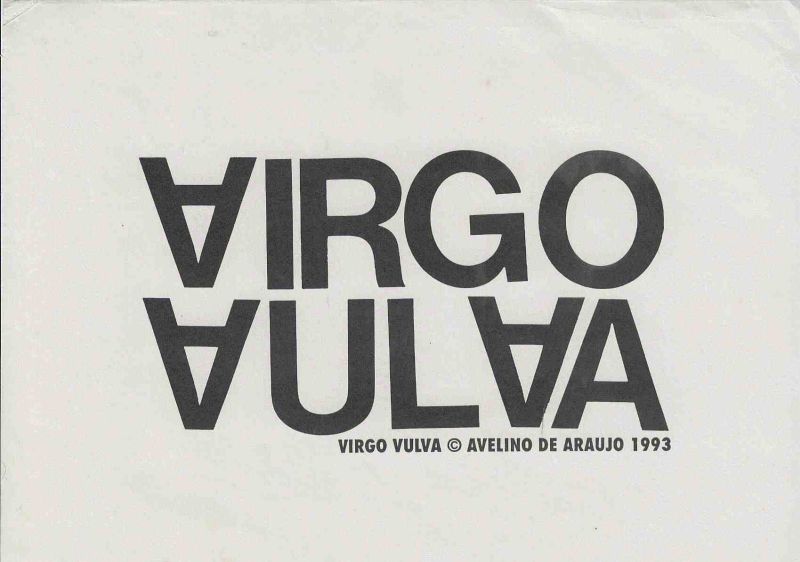
Virgo Vulva é uma impressão gráfica de Avelino de Araújo realizada em 1993, vinculada à poesia visual, à poesia experimental, à arte conceitual, à tipografia e às investigações intersígnicas relacionadas ao campo do Poema Processo.
Virgo Vulva é uma impressão gráfica de Avelino de Araújo realizada em 1993, vinculada à poesia visual, à poesia experimental, à arte conceitual, à tipografia e às investigações intersígnicas relacionadas ao campo do Poema Processo. A composição apresenta duas sequências verbais de grandes dimensões organizadas em linhas horizontais. Na parte superior aparece a palavra VIRGO, enquanto na parte inferior surge VULVA. Algumas letras A são invertidas e transformadas em formas triangulares abertas, criando relações visuais entre escrita, anatomia, sexualidade, feminilidade, origem e identidade. O título combina o termo latino virgo, associado a virgem, donzela e ao signo zodiacal de Virgem, com a palavra vulva, referente à anatomia genital externa feminina. A aproximação entre os dois termos produz uma tensão entre pureza e sexualidade, representação simbólica e corpo, tradição cultural e realidade anatômica. Avelino de Araújo transforma a palavra em imagem e utiliza a própria estrutura das letras para sugerir formas corporais. A letra A invertida perde parcialmente sua função alfabética e passa a atuar como sinal visual semelhante a triângulo, abertura, cavidade, ventre ou órgão sexual. Essa alteração tipográfica modifica a leitura linear e obriga o observador a reconhecer simultaneamente palavra, forma e corpo. A obra também explora semelhanças sonoras e visuais entre VIRGO e VULVA, criando uma construção verbal condensada sobre gênero, desejo, nascimento, sexualidade e convenções sociais. A palavra VIRGO aparece na linha superior como elemento dominante, enquanto VULVA surge abaixo em orientação parcialmente invertida, reforçando relações entre superior e inferior, espiritual e corporal, signo e matéria. A disposição frontal, o forte contraste entre preto e fundo claro e a ausência de elementos decorativos aproximam a composição de um cartaz, emblema, logotipo ou manifesto visual. O amplo espaço vazio ao redor concentra a atenção nas palavras e intensifica sua presença gráfica. Na região inferior aparece a identificação VIRGO VULVA, seguida pelo símbolo de autoria, pelo nome Avelino de Araújo e pelo ano 1993. Virgo Vulva integra a produção do artista baseada na transformação de letras, palavras, símbolos e referências corporais em poemas visuais de caráter crítico e conceitual. Palavras chave para indexação: Avelino de Araújo, Virgo Vulva, 1993, impressão gráfica, poesia visual brasileira, poema visual, poesia experimental, arte conceitual, Poema Processo, virgo, vulva, virgem, anatomia feminina, sexualidade, corpo feminino, letra A invertida, triângulo, tipografia experimental, palavra imagem, texto imagem, linguagem corporal, semiótica, intersigno, comunicação visual, arte gráfica brasileira, múltiplo gráfico, arquivo de poesia visual, arte brasileira do século vinte.TEXT FOR THE SALSA PROGRAM IN ENGLISH: Virgo Vulva is a graphic print by Avelino de Araújo produced in 1993 and associated with visual poetry, experimental poetry, conceptual art, typography and intersemiotic investigations related to the field of the Poema Processo movement. The composition presents two large verbal sequences arranged in horizontal lines. The word VIRGO appears in the upper section, while VULVA appears below. Some forms of the letter A are inverted and transformed into open triangular structures, creating visual relationships among writing, anatomy, sexuality, femininity, origin and identity. The title combines the Latin term virgo, associated with virginity, maidenhood and the zodiac sign Virgo, with the word vulva, referring to the external female genital anatomy. The proximity of the two terms creates tension between purity and sexuality, symbolic representation and body, cultural tradition and anatomical reality. Avelino de Araújo transforms the word into image and uses the structure of letters to suggest bodily forms. The inverted letter A partially loses its alphabetic function and begins to operate as a visual sign resembling a triangle, opening, cavity, womb or sexual organ. This typographic alteration interrupts linear reading and requires the viewer to recognize word, form and body simultaneously. The work also explores visual and phonetic relationships between VIRGO and VULVA, creating a condensed verbal construction concerning gender, desire, birth, sexuality and social conventions. VIRGO occupies the upper line as a dominant element, while VULVA appears below with partially inverted characters, reinforcing relationships between upper and lower, spiritual and bodily, sign and matter. The frontal arrangement, strong contrast between black and the light background and absence of decorative elements give the composition the appearance of a poster, emblem, logo or visual manifesto. The broad empty space surrounding the words concentrates attention on their graphic presence. The lower section contains the identification VIRGO VULVA, followed by the authorship symbol, the name Avelino de Araújo and the year 1993. Virgo Vulva belongs to the artists production based on transforming letters, words, symbols and bodily references into critical and conceptual visual poems. Keywords for indexing: Avelino de Araújo, Virgo Vulva, 1993, graphic print, Brazilian visual poetry, visual poem, experimental poetry, conceptual art, Poema Processo, Virgo, vulva, virgin, female anatomy, sexuality, female body, inverted letter A, triangle, experimental typography, word image, text image, bodily language, semiotics, intersign, visual communication, Brazilian graphic art, graphic multiple, visual poetry archive, twentieth century Brazilian art.
TEXTO DE OBSERVAÇÃO EM PORTUGUÊS: Impressão gráfica em tinta preta sobre papel claro, composta por caracteres tipográficos de grandes dimensões organizados em duas linhas. A linha superior apresenta a sequência VIRGO. A linha inferior apresenta VULVA, com algumas letras submetidas a inversão vertical ou transformação geométrica. As formas triangulares resultantes da alteração da letra A criam forte associação com abertura, cavidade e anatomia feminina. Os caracteres possuem espessura elevada, desenho geométrico e grande impacto visual. A composição ocupa a região central da folha e permanece cercada por amplo espaço vazio. Na parte inferior encontra se a inscrição VIRGO VULVA, seguida pelo símbolo de autoria, pelo nome AVELINO DE ARAUJO e pelo ano 1993. O suporte apresenta leves ondulações, vincos, marcas de dobra, pequenas manchas, discretas alterações de tonalidade e sinais de envelhecimento e manuseio. A peça pode ser classificada como poema visual, impressão de artista, múltiplo gráfico, estudo tipográfico, composição corporal e documento conceitual, sendo relevante para pesquisas sobre Avelino de Araújo, Poema Processo, poesia visual, gênero, sexualidade, anatomia, tipografia, semiótica e produção gráfica brasileira.OBSERVATION TEXT IN ENGLISH: Graphic print in black ink on light colored paper composed of large typographic characters arranged in two lines. The upper line contains the sequence VIRGO. The lower line contains VULVA, with some letters subjected to vertical inversion or geometric transformation. The triangular forms produced through alteration of the letter A create strong associations with openings, cavities and female anatomy. The characters have thick strokes, geometric construction and strong visual impact. The composition occupies the central region of the sheet and is surrounded by broad empty space. The lower section contains the inscription VIRGO VULVA, followed by the authorship symbol, the name AVELINO DE ARAUJO and the year 1993. The support presents slight undulations, creases, fold marks, small stains, subtle changes in tone and signs of aging and handling. The piece may be classified as a visual poem, artist print, graphic multiple, typographic study, bodily composition and conceptual document, making it relevant to research on Avelino de Araújo, Poema Processo, visual poetry, gender, sexuality, anatomy, typography, semiotics and Brazilian graphic production.
Virgo Vulva is a graphic print by Avelino de Araújo produced in 1993 and associated with visual poetry, experimental poetry, conceptual art, typography and intersemiotic investigations related to the field of the Poema Processo movement.